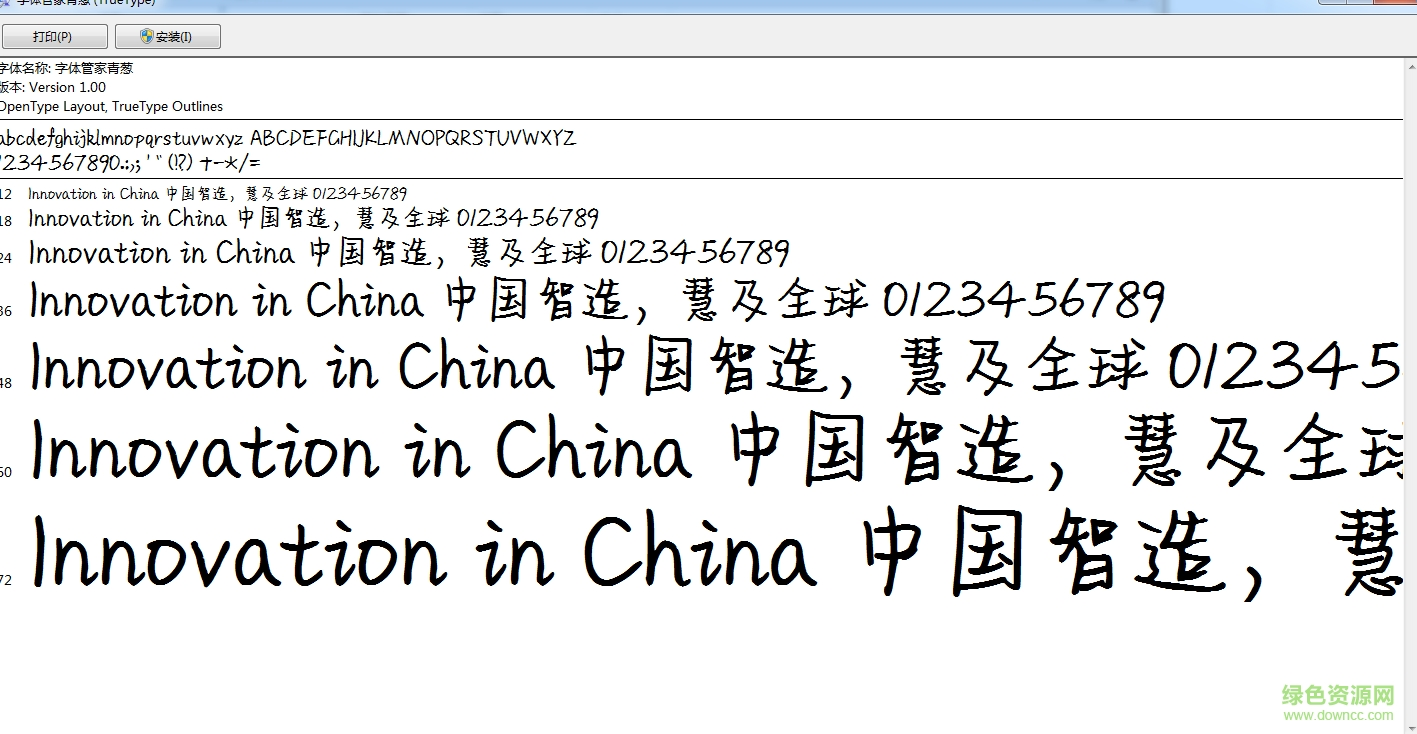
字體管家青蔥字體
字體管家青蔥字體是一款相當(dāng)實(shí)用的其他字體,字體的形式十分美觀筆畫生動(dòng)活潑,可用于創(chuàng)意設(shè)計(jì)或廣告設(shè)計(jì)方面,感興趣就趕緊來綠色資源網(wǎng)下載體驗(yàn)!
字體管家青蔥字體適用領(lǐng)域
字體管家青蔥字體適用于產(chǎn)品包裝、電視臺(tái)廣告、電影、電視劇片頭以及內(nèi)容用字等領(lǐng)域